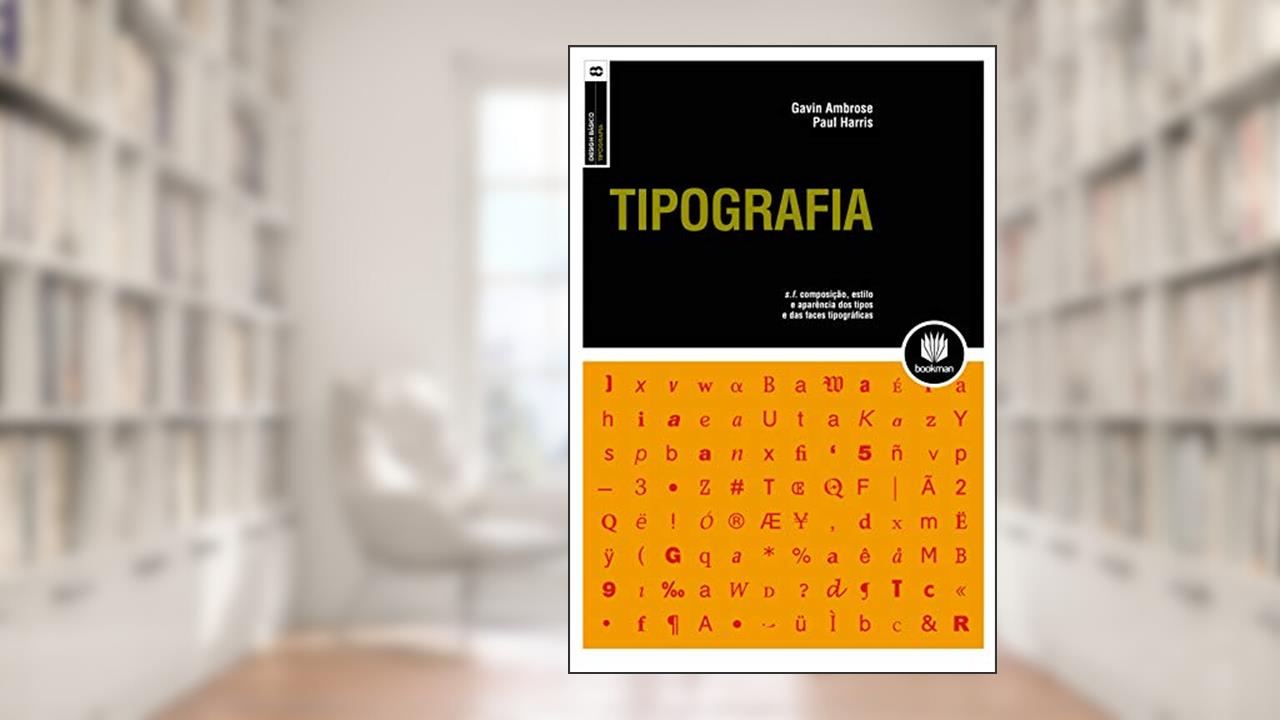
Tipografia não é apenas um simples estudo sobre letras. É uma imersão fascinante em um universo que molda a comunicação visual e estimula a criatividade. Gavin Ambrose e Paul Harris, com maestria, revelam como a tipografia vai além da estética e se transforma em um poderoso veículo de expressão. Este livro é como um portal que te transporta para as sutilezas de um campo que, muitas vezes, passa despercebido, mas que é vital para a forma como nos conectamos e interagimos com o mundo ao nosso redor.
Ao abrir as páginas de Tipografia, você é bombardeado por uma explosão de informações e insights que fazem o coração do designer pulsar mais rápido. Os autores exploram a evolução das letras, desde suas origens até a era digital, provocando uma reflexão intensa sobre a importância da escolha tipográfica no design gráfico, na publicidade e na arquitetura da informação. Cada tipo de letra não é apenas uma forma; é uma identidade, uma emoção, uma mensagem. E isso é o que torna este livro tão impactante.
Os comentaristas e leitores não hesitam em exaltar o poder transformador da obra. Muitos afirmam que Tipografia mudou a forma como percebem o design, destacando como cada fonte utilizada em um projeto pode ser a diferença entre uma mensagem bem compreendida e uma comunicação falha. Outros, no entanto, criticam o livro por sua abordagem técnica e às vezes densa, apontando que pode afastar os leigos que buscam uma compreensão mais intuitiva da tipografia.
Mas, se você está disposto a se aprofundar, será recompensado. A obra nos ensina que a tipografia não é um mero detalhe, mas sim um componente essencial da narrativa visual. Aprender sobre kerning, espaço, peso e estilo das fontes é um convite para que você enxergue cada texto com novos olhos. É um grito silencioso que ecoa no design contemporâneo, moldando nossas percepções e, em última análise, a cultura visual que nos cerca.
Como um soco no estômago, Tipografia desafia o status quo, empurrando você a repensar como as palavras e formas se entrelaçam para criar experiências significativas. Ambrose e Harris não estão aqui apenas para educar, mas para incitar uma revolução no jeito como percebemos a comunicação visual. E você, leitor, não pode se dar ao luxo de ignorar essa chamada.
Ao mergulhar nesta leitura, você descobrirá que, por trás de cada letra, há uma história esperando para ser contada. Você será levado a refletir sobre a responsabilidade que cada designer carrega ao escolher sua tipografia, tocando em questões de acessibilidade, legibilidade e impacto emocional. Prepare-se para se ver desafiado, instigado e, acima de tudo, inspirado a explorar o mundo da tipografia com um olhar renovado e apaixonado. A sabedoria contida neste livro pode ser a chave para libertar sua criatividade e abrir portas que você nem sabia que existiam. Não perca essa chance de transformar sua maneira de ver e viver a tipografia!